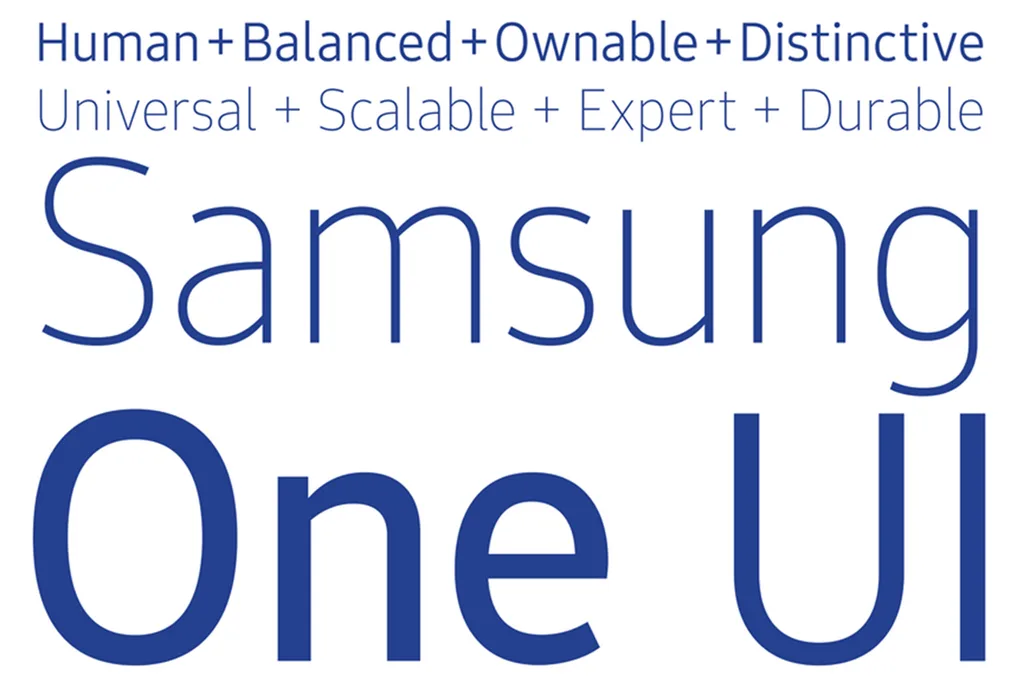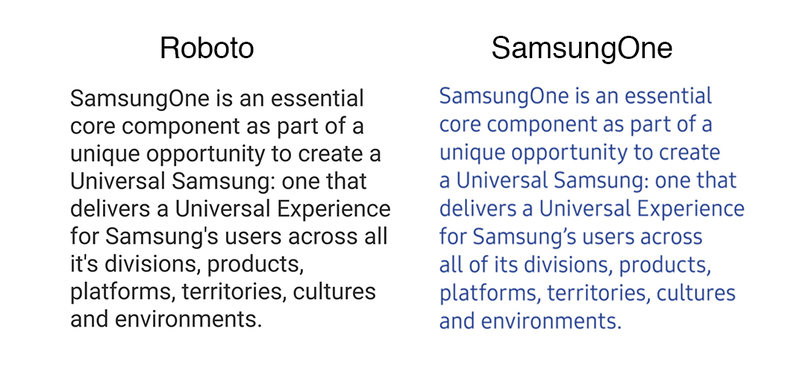
Teknoloji dünyasının büyük şirketlerinin kendi özel yazı tiplerini geliştirmeleri pek sıra dışı bir durum değil. Google “Roboto” adını taşıyan bir yazı tipi ailesi tasarlamış ve bu aile şirketin Material Design çerçevesinde hazırladığı uygulamaların temel taşlarından biri olmuştu. Apple ise “San Francisco” ismindeki yazı tipini bir süre önce tüm Apple cihazlarında varsayılan hâle getirmişti. Microsoft, “Segoe” isimli yazı tipini kendi bünyesinde geliştirmedi. Ancak söz konusu yazı tipi Microsoft, Windows ve Office markalandırmasında önemli bir yerde duruyor.
Samsung da bu kervana SamsungOne adını verdiği özel yazı tipiyle katılıyor. Şirket, bu yazı tipiyle geniş bir alanı kapsayan ürünlerine tutarlı ve evrensel bir görsel kimlik kazandırmayı amaçlıyor. Güney Koreli şirketin farklı kategorilerdeki ürünlerinde kullanılacak yazı tipini, reklamlarda da görmek mümkün olacak. Yazı tipi 25 binden fazla karakteri ve 400 farklı dili destekleyecek.
SamsungOne görüntü itibarıyla orijinal Android yazı tipine benziyor
Samsung’un yeni yazı tipi, akıllara Android’in orijinal yazı tipi “Droid Sans”ı getiriyor. Ancak Google’ın yeni yazı tipi Roboto ve SamsungOne arasında da bazı küçük benzerliklerin olduğu söylenebilir.
Samsung yeni yazı tipini ne zaman kullanıma sunacağı konusunda kesin bir takvim açıklamadı. Ancak şirketin gelecek hafta tanıtılacak Galaxy Note 7’de yeni yazı tipine yer verebileceği belirtiliyor.